Font chữ bao cấp đang trở lại như một trào lưu thiết kế hoài niệm đầy sức hút. Với nét chữ vuông vức, thô mộc, nó gợi nhớ biển hiệu, áp phích của thời kỳ xưa cũ. Không chỉ hoài cổ, kiểu chữ này còn trở thành xu hướng sáng tạo nổi bật trong năm 2026.
Xu hướng font chữ bao cấp quay lại
Font chữ bao cấp là kiểu chữ được lấy cảm hứng từ những biển hiệu, áp phích tuyên truyền, tem phiếu thời kỳ bao cấp ở Việt Nam. Nét chữ vuông vức, thô mộc nhưng đầy tính biểu tượng đã trở thành một phần ký ức thị giác của nhiều thế hệ.
Trong vài năm gần đây, kiểu font thời bao cấp bất ngờ quay trở lại và gây sốt trong cộng đồng thiết kế lẫn giới trẻ. Sự hoài niệm kết hợp cùng phong cách vintage, retro khiến font chữ bao cấp được ưa chuộng trong poster phim, bìa sách, ảnh chế hay các chiến dịch truyền thông.
Đặc biệt, nhiều nhà thiết kế còn kết hợp font chữ bao cấp với các bộ sưu tập font chữ đẹp miễn phí để tạo nên sự mới mẻ, độc đáo. Trên mạng xã hội, đây cũng là trào lưu thú vị, vừa gợi nhớ ký ức xưa, vừa tạo sự khác biệt trong sáng tạo nội dung.
Điểm nhấn của font chữ bao cấp
Các điểm nhất của font chữ này có thể kể đến như:
Nét chữ vuông vức, thô mộc, gợi nhớ biển bảng cũ
Theo Font Chuẩn, Font chữ bao cấp tái hiện những đường nét vuông vắn, mạnh mẽ và có phần thô mộc, giống như các biển bảng, áp phích tuyên truyền của thời kỳ bao cấp. Chính sự mộc mạc này lại mang đến một sức hút riêng, giúp người xem ngay lập tức liên tưởng đến bối cảnh lịch sử đặc biệt.
Gợi cảm giác hoài niệm, vintage, “retro Việt Nam”
Điểm thú vị của font chữ này là nó không chỉ gợi nhắc về quá khứ, mà còn mang đậm chất vintage và retro Việt Nam, khác biệt với các font retro phương Tây. Vì thế, khi sử dụng trong thiết kế, nó tạo ra sự gần gũi, thân quen mà vẫn rất cá tính và nổi bật.
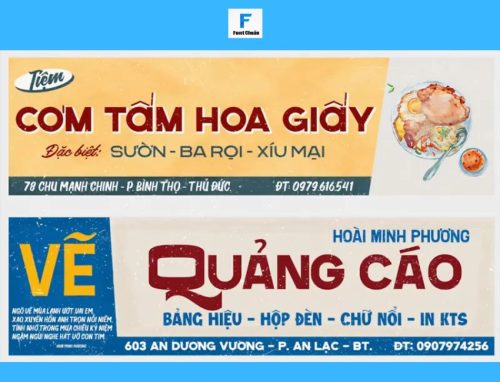
Phù hợp làm poster, bìa sách, thiết kế sáng tạo mang phong cách cổ điển
Nhờ tính chất hoài cổ nhưng độc đáo, font chữ bao cấp thường được dùng trong poster phim, bìa sách, ấn phẩm quảng cáo, hoặc thiết kế sáng tạo theo phong cách cổ điển. Đây là lựa chọn lý tưởng cho những ai muốn thổi hồn ký ức vào sản phẩm thiết kế, tạo nên sự khác biệt và ấn tượng.
Ứng dụng thực tế
Sử dụng trong quảng cáo, thiết kế thương hiệu gợi nhớ ký ức
Không ít nhãn hàng tận dụng font chữ bao cấp trong quảng cáo và xây dựng thương hiệu, đặc biệt là các sản phẩm gắn với ký ức tập thể như đồ ăn vặt tuổi thơ, quán cà phê retro, hay thương hiệu mang màu sắc vintage. Nhờ đó, font chữ này giúp doanh nghiệp tạo sự kết nối cảm xúc mạnh mẽ với khách hàng.
Dùng trong poster phim, MV ca nhạc mang màu hoài cổ
Font chữ bao cấp thường xuyên xuất hiện trong poster phim, MV ca nhạc lấy bối cảnh xưa cũ, nhằm tạo bầu không khí hoài cổ, gần gũi với khán giả. Chỉ cần nhìn qua kiểu chữ, người xem đã có thể cảm nhận được tinh thần của thời kỳ bao cấp mà tác phẩm muốn tái hiện.
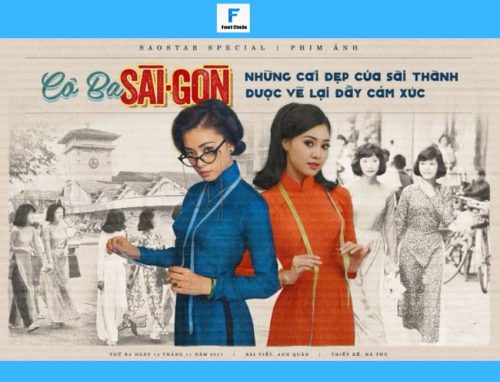
Viral trên TikTok/Facebook qua meme và ảnh chế
Trên mạng xã hội, font chữ bao cấp nhanh chóng trở thành một trend thú vị, xuất hiện trong meme, ảnh chế, caption hài hước. Phong cách chữ mộc mạc, “cổ điển” nhưng lồng ghép trong bối cảnh hiện đại tạo ra sự đối lập hài hước, khiến giới trẻ thích thú và chia sẻ rầm rộ.
Font chữ bao cấp gắn liền với các ấn phẩm in ấn của một giai đoạn đã qua, nơi hình khối chữ được đặt lên hàng đầu. Khi bước sang môi trường số, tư duy về typography cũng thay đổi đáng kể, đặc biệt trong các không gian giải trí. Font chữ Minecraft là ví dụ rõ nét cho cách chữ được thiết kế để phù hợp với thế giới game và pixel art.
Tổng hợp 20+ Font chữ bao cấp trong các banner/ quảng cáo/ biển hiệu xưa
Nếu bạn muốn tái hiện lại không khí hoài niệm của thập niên bao cấp, những font chữ trong banner, quảng cáo và biển hiệu xưa dưới đây chắc chắn sẽ là lựa chọn hoàn hảo.
Font chữ thời kì bao cấp trên vỏ/ bìa quảng cáo
Những tấm bìa, bao bì quảng cáo thời bao cấp thường sử dụng font chữ vuông vức, dày nét, tạo cảm giác chắc chắn và nổi bật. Kiểu chữ này vừa mộc mạc, vừa mang hơi thở của thời kỳ cũ.
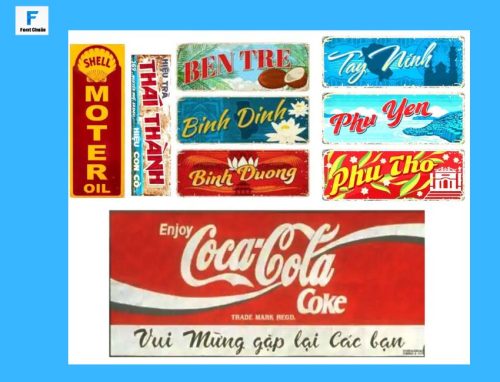
Font chữ thời kì bao cấp tên quán/ banner
Tên quán, biển hiệu hay banner thời bao cấp thường dùng font chữ in hoa, to rõ, dễ nhìn từ xa. Đây là đặc trưng giúp khách hàng dễ nhận biết và tạo nên phong cách retro độc đáo khi tái hiện ngày nay.
Một số font chữ cùng thời khác
Ngoài font chữ vuông vức, còn có những kiểu chữ nghiêng nhẹ, nét thanh – nét đậm hoặc chữ viết tay giản dị. Những font này gắn liền với báo chí, áp phích tuyên truyền và biển hiệu dân dụng thời bao cấp.
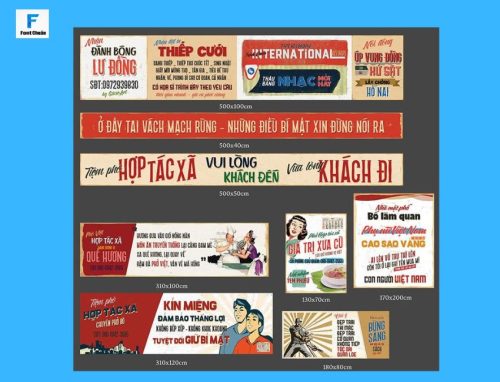
Việc tìm hiểu và sử dụng các font chữ bao cấp không chỉ giúp bạn gợi nhớ về một thời kỳ hoài niệm mà còn mang lại nét độc đáo, khác biệt cho các thiết kế hiện đại. Bộ sưu tập 20+ font chữ trên sẽ là nguồn cảm hứng tuyệt vời để bạn áp dụng trong banner, quảng cáo hay biển hiệu, vừa giữ nét retro, vừa tạo điểm nhấn ấn tượng cho dự án sáng tạo của mình.